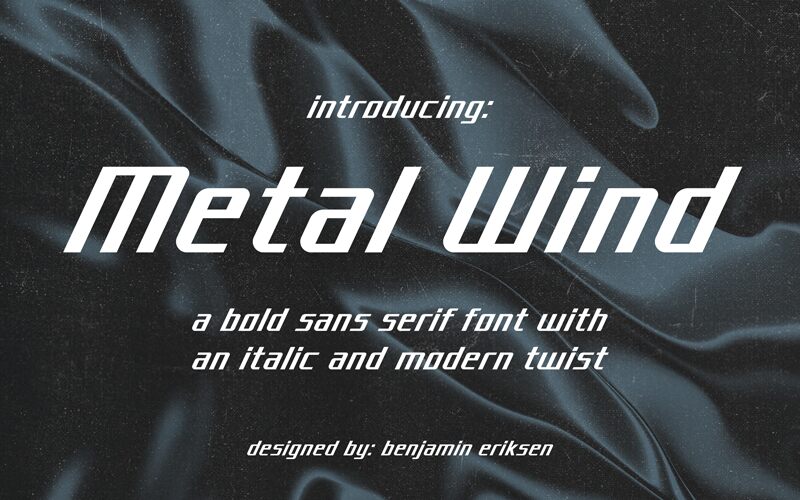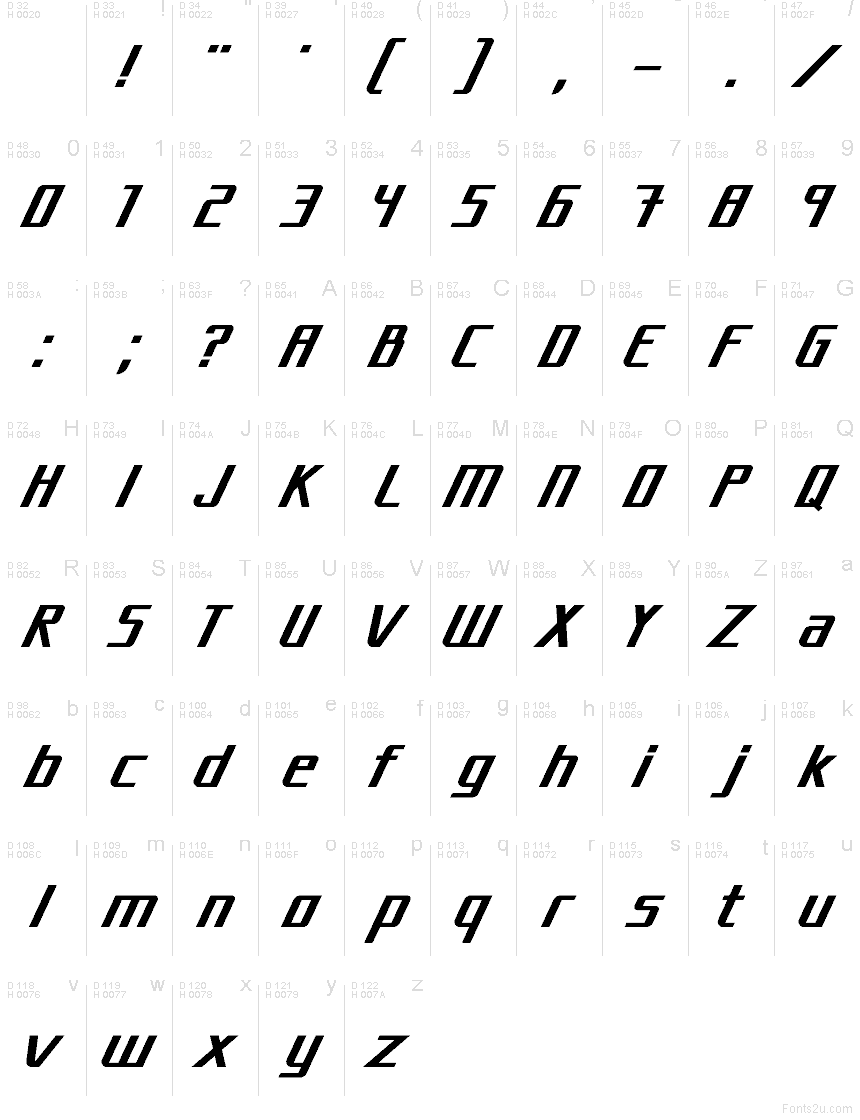
Metal Wind
Metal Wind est une police d'affichage gratuite de style techno, caractérisée par des formes inclinées et découpées ainsi qu'un rythme industriel épuré. Ses contours sont acérés sans être rigides, offrant des contreformes ouvertes et un élan vers l'avant qui confère aux lettres une cadence mécanique rapide.
Metal Wind est idéale pour les titres de science-fiction, les visuels d'esport, les affiches, les pochettes d'albums et toute identité de marque nécessitant une touche numérique. Cette police gratuite convient également aux emballages, logos et étiquettes produits, car sa structure angulaire assure une présence technique affirmée sans recourir à l'ornement.